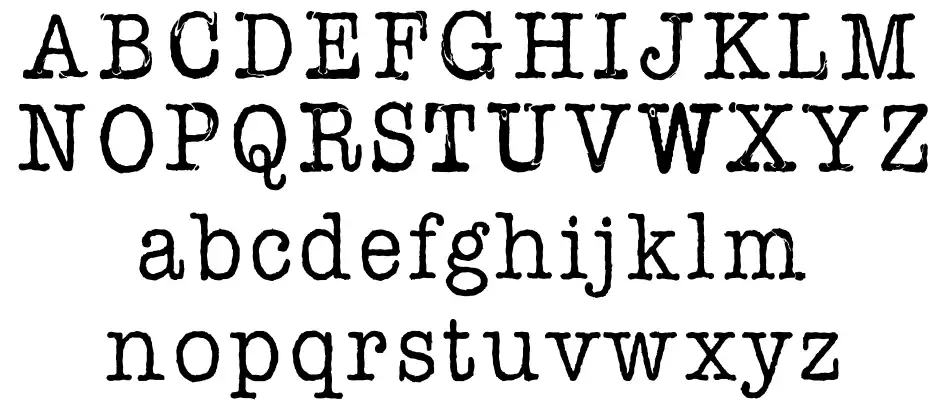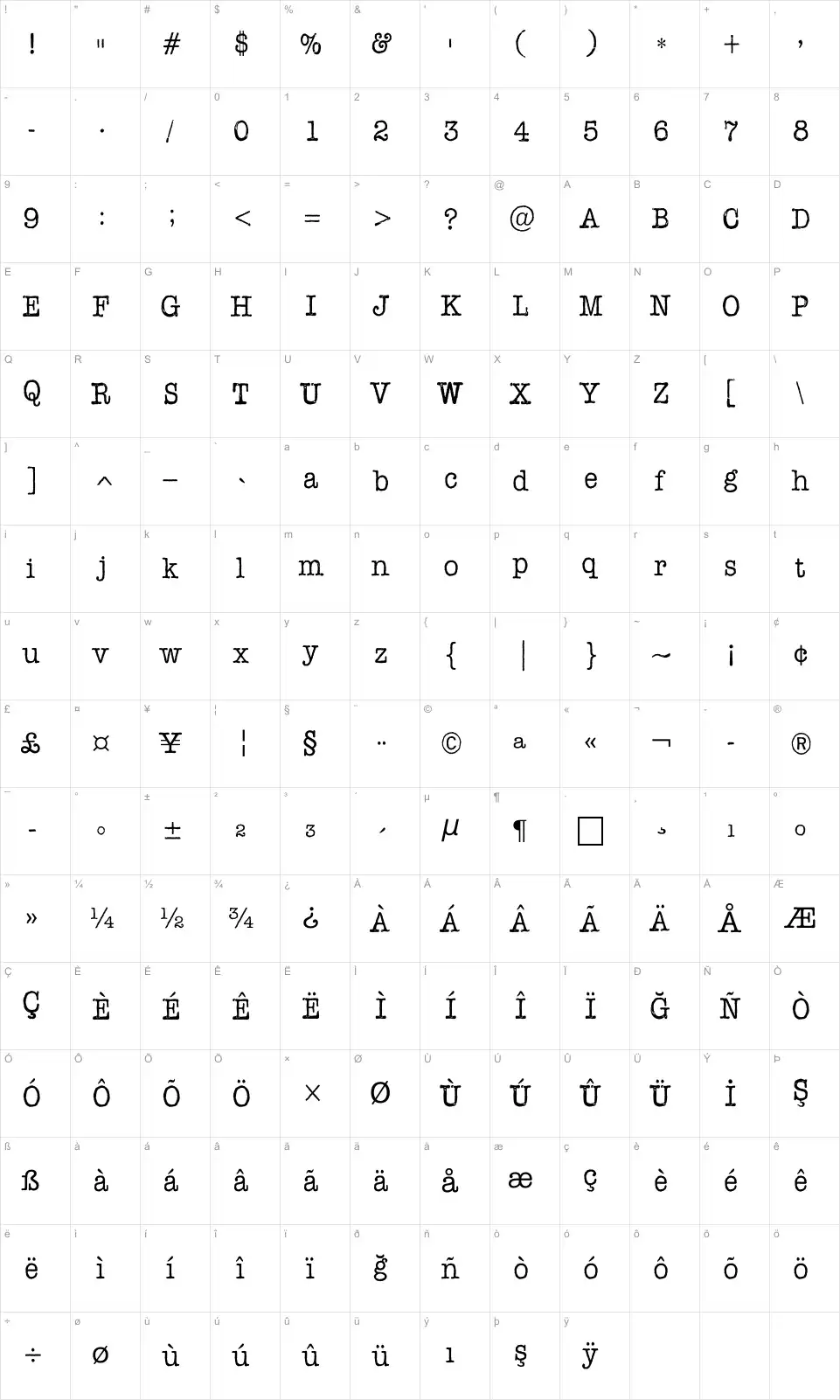
AFL Font Pespaye Nonmetric – Download Grátis
A AFL Font Pespaye Nonmetric, criada pelo designer Burkay Demirci, é uma fonte Fancy inspirada em tipografia typewriter. Esta fonte é gratuita, disponível em formato TTF, e pertence à categoria de Typewriter. Com seu design elegante e arredondado, ela oferece um toque moderno à escrita, ideal para aqueles buscando um estilo único em seus trabalhos digitais. A fonte já tem 2300 downloads e seu tamanho compacto de 81 KB a torna conveniente para uso em dispositivos móveis ou computadores. Se você está procurando por uma fonte que combine facilidade de uso com um design arredondado e minimalista, a AFL Font Pespaye Nonmetric pode ser uma ótima escolha. Não hesite em visitar o site do designer, https://www.burkaydemirci.com, para explorar mais de seus trabalhos criativos.